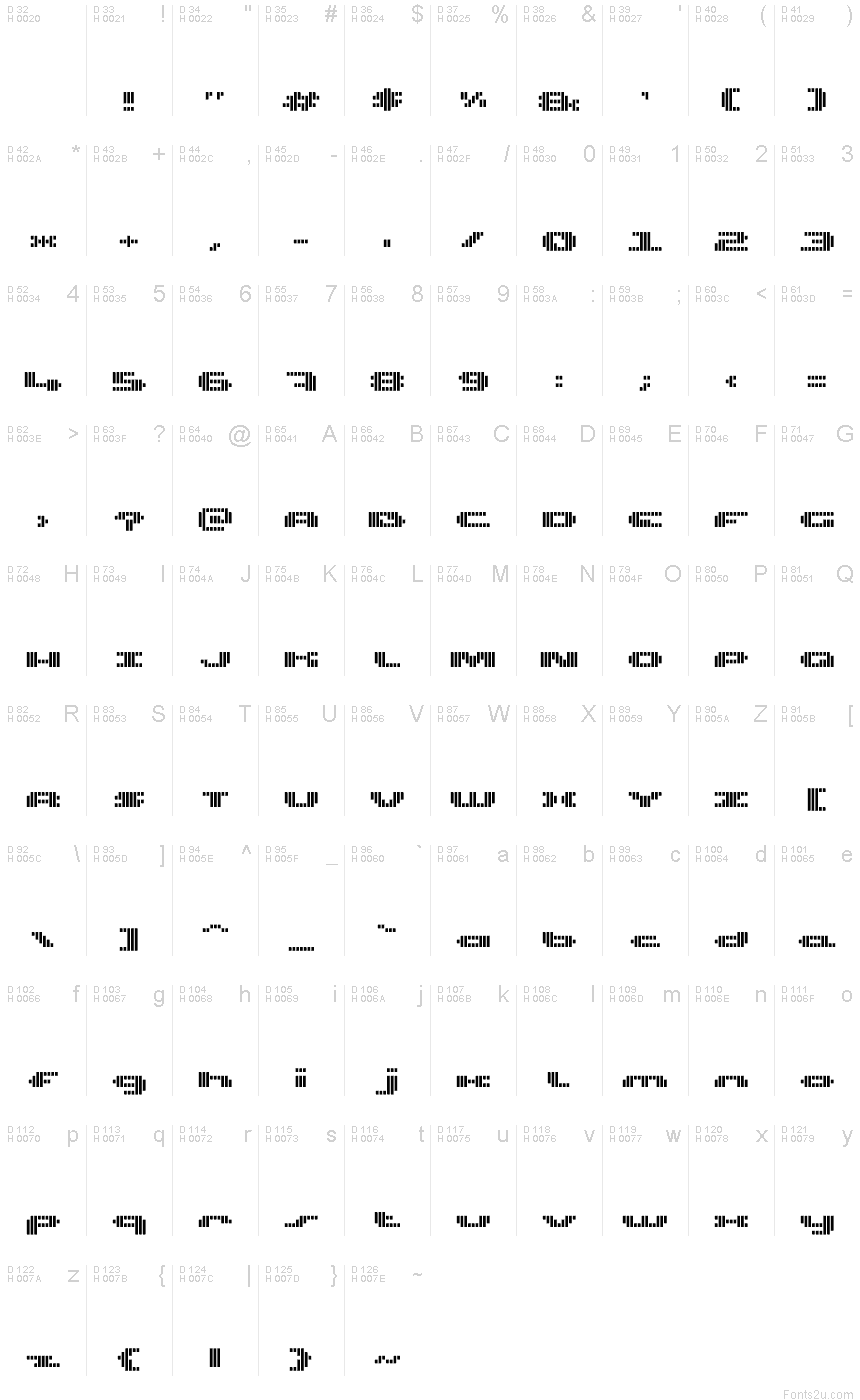
UP Tiny lcd four 8 decoV من تصميم UrbanPixel هو خط رقمي مجاني للعناوين، يجمع بين لمسة شاشات LCD وأجواء ألعاب الآركيد الكلاسيكية. الحروف مبنية من أشرطة عمودية سميكة ونقاط مربعة صغيرة، مما يمنحها إيقاعاً هندسياً يذكرنا بلوحات النتائج القديمة وشاشات الأجهزة المحمولة الأولى.
هذا ما يجعله خياراً طبيعياً لشعارات الألعاب، ومنشورات موسيقى الـ Chiptune، وعناوين الملصقات، وأغلفة الموسيقى، وهويات العلامات التجارية التقنية القديمة؛ حيث يمكن لخط مجاني يتمتع بهذا النبض المربع أن يحقق تأثيراً كبيراً باستخدام القليل من الحروف فقط. كما أنه يعمل بشكل ممتاز لبطاقات العناوين وتسميات الواجهات القصيرة، حيث يجعل نمط الأشرطة والنقاط المتكرر كل كلمة تبدو وكأنها مبرمجة عن قصد.